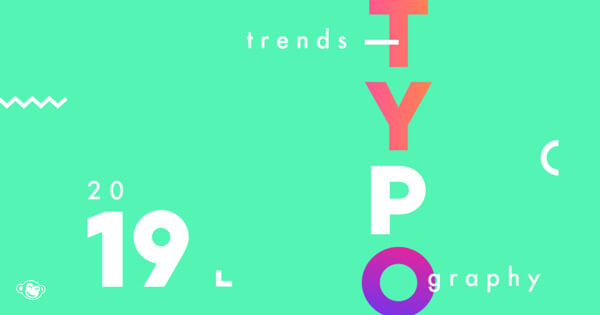
字体の組み合わせで、デザインを美しくする方法
字体を組み合わせることは芸術です。芸術やデザインにおいて一番いいのは、一旦形を作ってから、いいたい事を伝えるにはどのような形にすればいいか模索していくようにすることです。そうは言っても、これらの作業をするには、字体デザインの基本を知らなければいけません。
デザイナーは、視覚的に興味を引くためと、必要な情報を強調するために、複数のフォントを使います。これは難しくなく、科学的なルールがあります。よい字体にするために、何度か試してみることが大切です。デザインのいい例をいくつか見ることで、どれを組み合わせればいいか、どうすればうまくいくかわかります。
1. フォントの組み合わせ
大抵の字体は、ユーザーの気持ちを動かすことができます。それぞれの字体には、個性があるので、うまく組み合わせなければなりません。あなたは、あなたのデザインに合う字体を探したいと思っているはずです。その一方で、気に入った字体を使い続けたいという気持ちもあると思います。
通常、これらのバランスを取ってデザインされます。例えば、上のようなボールドのはっきりした字体には、細い上品な字体を組み合わせます。これは、字体の組み合わせで、よく使われる手法です。これは、自分の感覚に頼ることが多いのですが、それでいいのです。バランスのいい組み合わせを探す作業は、何度かやる必要がありますが、時間がたてば、簡単にできるようになります。
2.セリフ有り無しの組み合わせ
これは、ウェブでも印刷物でもよく使われている組み合わせです。もし時間がなければ、セリフのあるものとないものを組み合わせると、読みやすいデザインになります。ですが、太字の字体と組み合わせないほうがいいです。
たとえば、下の例を見ると、トレードゴシックがダイナミックで、ベルゴシックが上品な字体なので、トレードゴシックが主張しすぎます。この2つの字体は、読みやすい組み合わせではありません。この組み合わせは、あまり読みやすくありません。
3.コントラストをつける
セリフ有り無しを組み合わせる理由のひとつが、組み合わせることでコントラストができるという事です。コントラストはさまざまな方法で作ることができます。たとえば、色、形、比重、大きさや余白などです。上の例だと、丸い太字と細い字体を組み合わせることで、見栄えがよくなっています。
4.見栄えをよくする
もしあなたが、デザインのプロジェクトを行うとき、レイアウトやイメージだけでなく、本文も考えなければいけません。見る人にとって一番重要なのは本文だからです。どの情報をデザインの主要部分に入れるかを考えるのが一つの方法です。重要なものをどこに置くかを決めれば、より伝わりやすいデザインになります。新聞、雑誌、同人誌のような形が決まっているものは、レイアウトのいい例になります。
5.フォント数を制限する
フォントの数は1デザインにつき2か3にするのが望ましいです。そうすると、全体的に読みやすくなります。しかし、いくつかのプロジェクトは、フォントをいくつも組み合わせる必要があるかもしれません。この場合は、あなたのデザインが調和されているようにしなければなりません。
6.文脈を考える
テキストは、デザインのプロジェクトにおいて重要な部分です。読みやすく、見やすいフォントサイズでなければいけません。フォントの形も全体の雰囲気を決めるのに重要です。字体の特徴が、あなたが伝えたい事と合っている必要があります。ポップに伝えたいときはポップに、ニュートラルな感じにしたいときはニュートラルにしなければいけません。
7.割り当て
字体を組み合わせる簡単な方法のひとつが、それぞれ違う役割で使うやり方です。たとえば、見出しに太字を使い、時々それをコピーして使い、本文には別の字体を使います。最後に一緒にした時、まとまりのあるデザインにならなければなりません。このように自分自身でルールを作ることで、強調したい部分がはっきりしてきます。
8.違うサイズを使う
コントラストを付ける一番いい方法は、文字の大きさを変えることです。これで、とても見やすくなります。上の例で見ると、左側より右側のほうが見やすくなっています。文字の大きさを調整することで、見やすくなります。
まとめ
これまでいくつかの字体を組み合わせる方法を紹介しましたが、明確な決まりはありません。これらの方法は、あなたがデザインする時に役に立つはずです。何度も練習すれば、よくなってきます。フォントを組み合わせる事は、直観力と経験が必要で、リスクを伴います。これまで教えた方法が、あなたのデザインのヒントになれば幸いです。